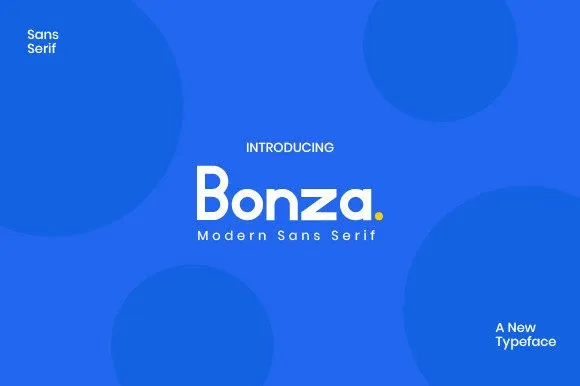
Bonza Font – Download Grátis
A “Bonza Font” é uma tipografia sans-serif moderna, desenvolvida com formas geométricas que foram corrigidas ópticamente para melhorar a legibilidade. Suas linhas retas e sua forma puramente geometrica o tornam um recurso ideal para projetos de gráficos variados. Esta fonte pode facilmente ser combinada com uma ampla gama de aplicativos, então use-a para destacar suas ideias criativas! Será impressionante ver como ela destaca seus trabalhos. Não perca esta oportunidade de dar um novo impulso à sua identidade visual e gráfica.